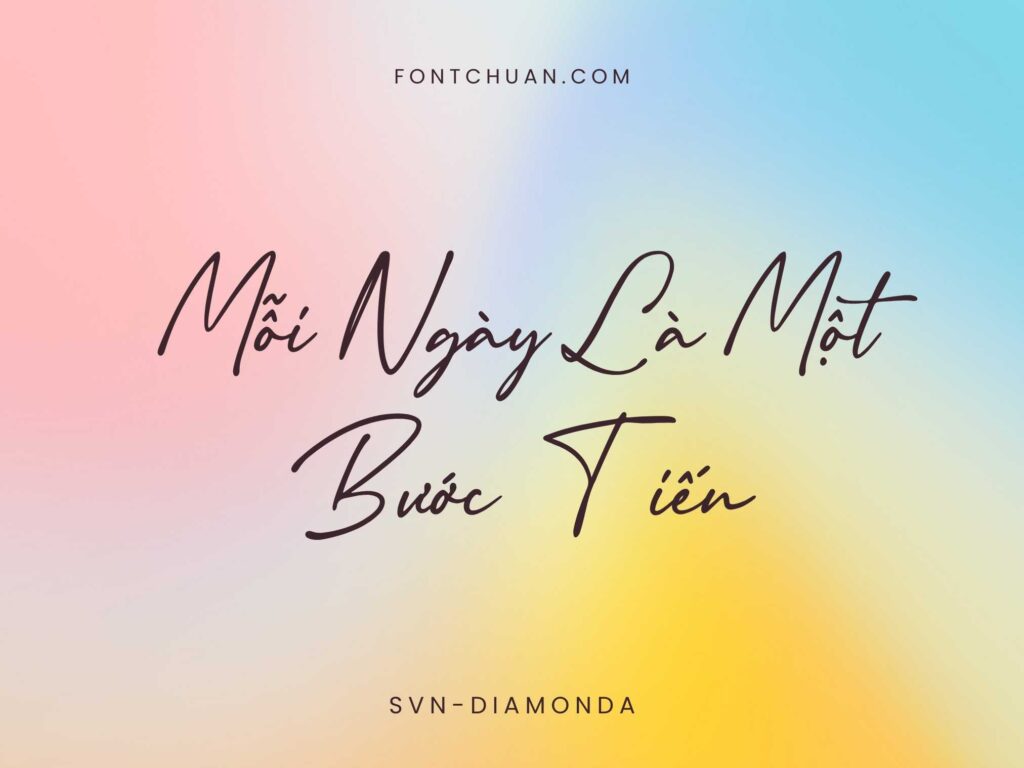
Font SVN Diamonda Việt Hóa
Tác giả Font: Bangkit Tri Setiadi
Diamonda là một font chữ viết tay hiện đại, được thiết kế bởi Blankids Studio. Font này mang lại cảm giác vui tươi và tự nhiên, phù hợp cho các dự án thiết kế như tiêu đề, logo, thiệp mời, áo thun, trích dẫn và nhiều ứng dụng khác. Font đã được Việt hóa để hỗ trợ tiếng Việt bởi STYLEno.1 Fonts, đồng thời hỗ trợ nhiều ngôn ngữ khác, giúp mở rộng phạm vi sử dụng trên toàn cầu. Font này được chia sẻ miễn phí cho mục đích sử dụng cá nhân; để sử dụng cho mục đích thương mại, bạn nên mua bản quyền từ nhà phát hành.
Đặc điểm thiết kế của Diamonda bao gồm các nét chữ viết tay mềm mại và thanh lịch, tạo cảm giác thân thiện và gần gũi. Font này phù hợp cho các ứng dụng như tiêu đề, logo, thiệp mời, áo thun, trích dẫn và nhiều dự án sáng tạo khác. Các ngành nghề phù hợp bao gồm quảng cáo, nghệ thuật và thiết kế đồ họa.